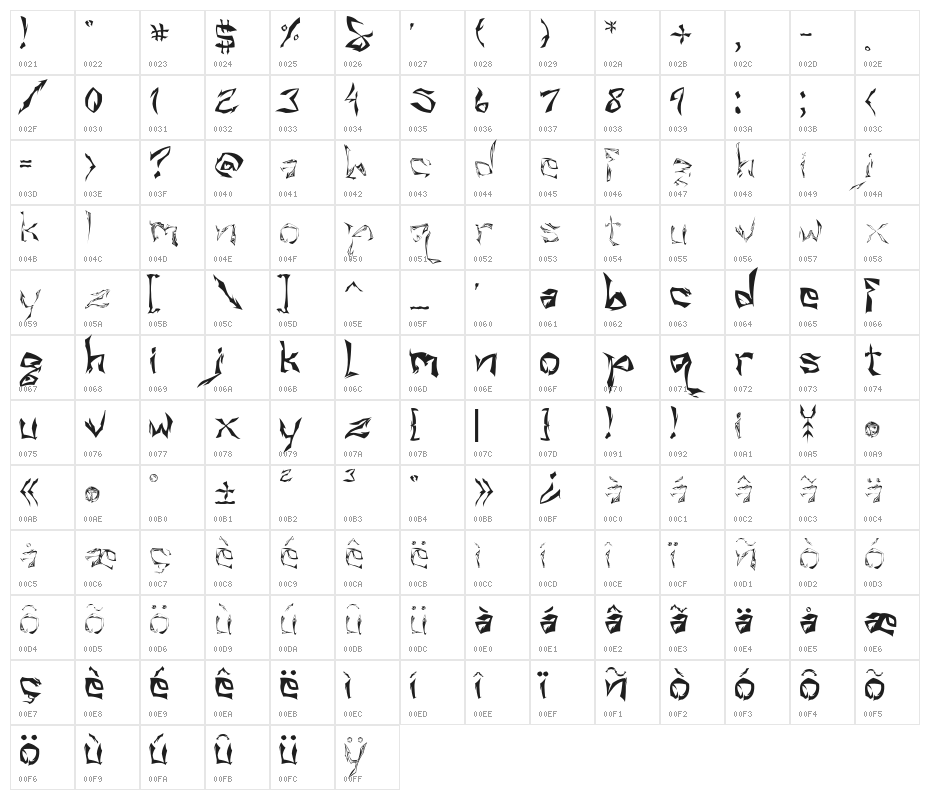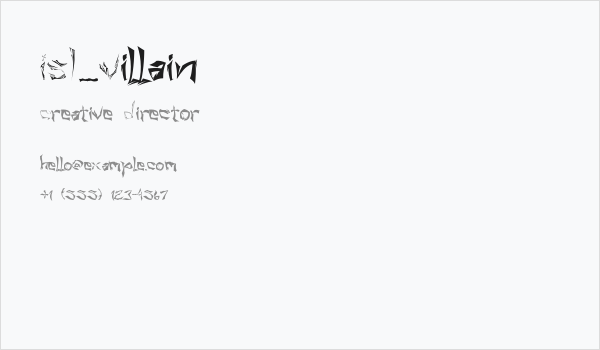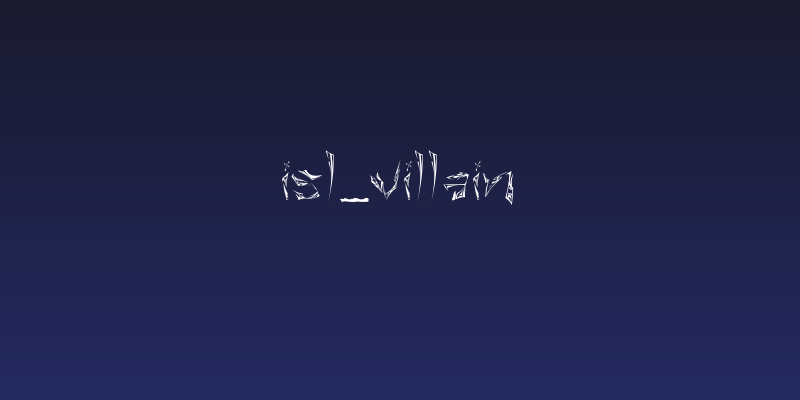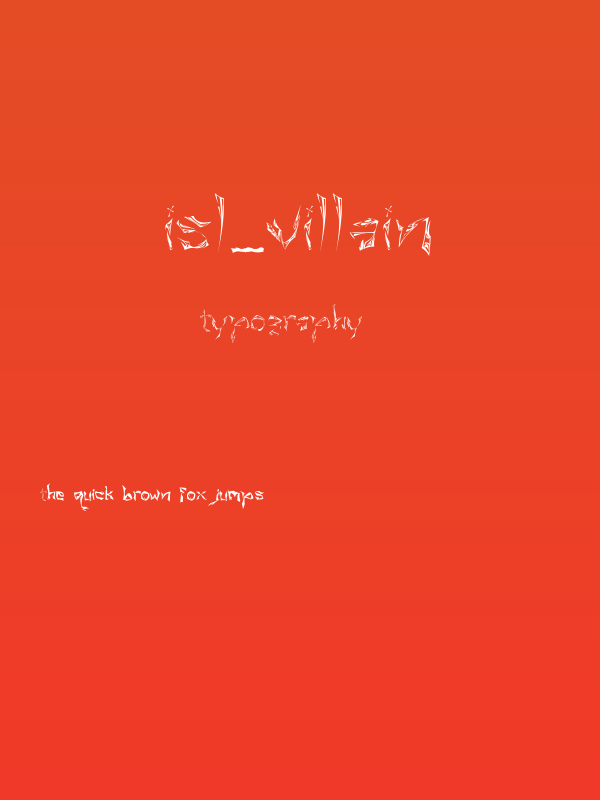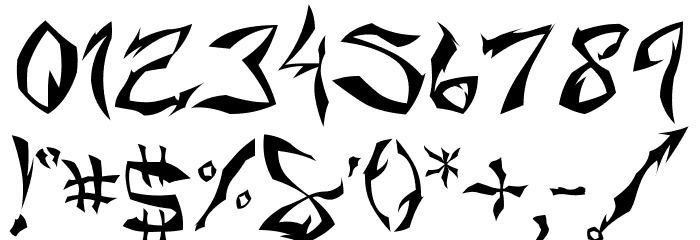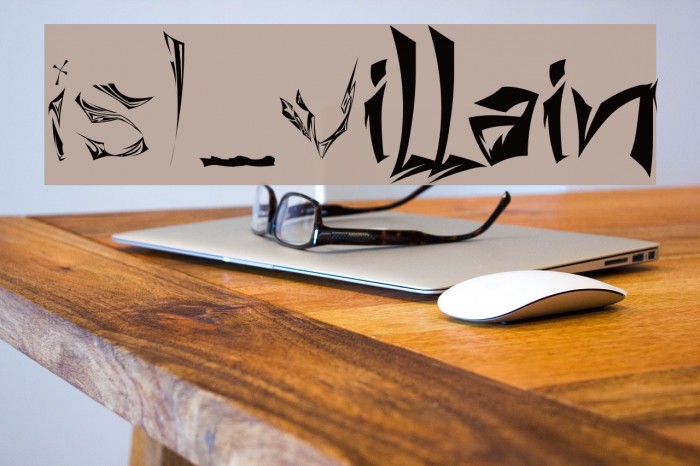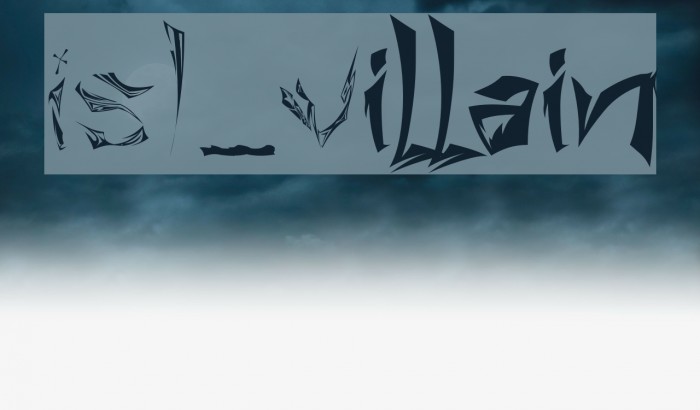
ISL_Villain Font
Isurus Labs - Derik Schneider
| Estilo geral | Modern, Edgy |
| Projetos propostos | Ideal for music album covers, video game titles, posters, and branding for edgy or alternative products. |